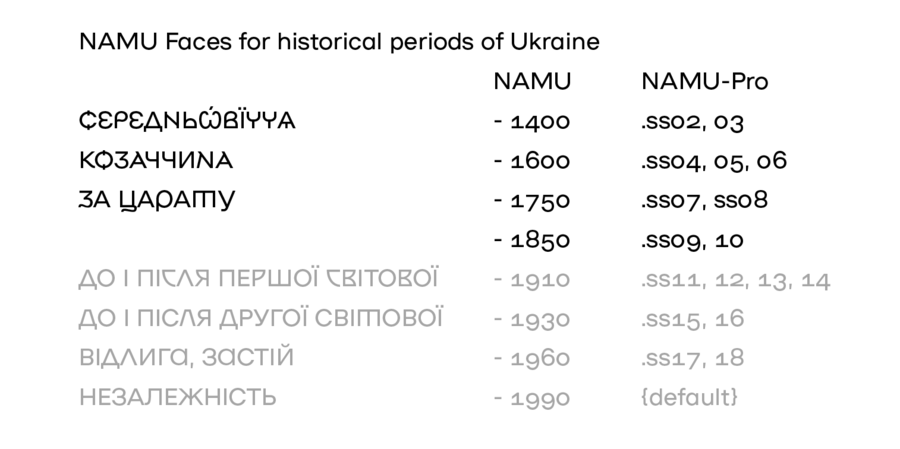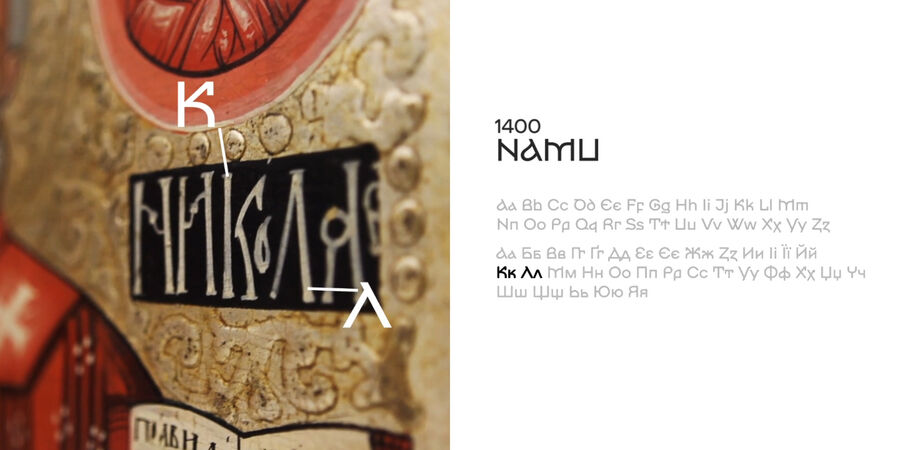
NAMU Old Style – шрифти 1400, 1600, 1750, 1850 з безкоштовної гарнітури для Національного художнього музею України. NAMU – геометричний гротеск зі смаколиками, херітажем, челенджьом та таймлайном. Переможець Red Dot 2019 у категорії «Корпоративний дизайн та айдентика». Наприкінці 2018 року Національний художній музей України та Banda презентували нову айдентику. Шрифт NAMU став основою візуального стилю. Для створення шрифту дизайнер Дмитро Растворцев з головою занурився у дослідження музейного фонду, архівних документів і накреслень стародавніх літер. У результаті фінальний шрифт NAMU має 20 стилістичних наборів у версії NAMU Pro та 9 окремих накреслень для кожного історичного періоду. Усі шрифти NAMU є безкоштовними для комерційного та некомерційного використання. Але файли шрифтів не можна декомпілювати. Ліцензія Creative Commons CC BY-ND 4.0. Шрифт розробив Дмитро Растворцев у 2018-2022 роках.